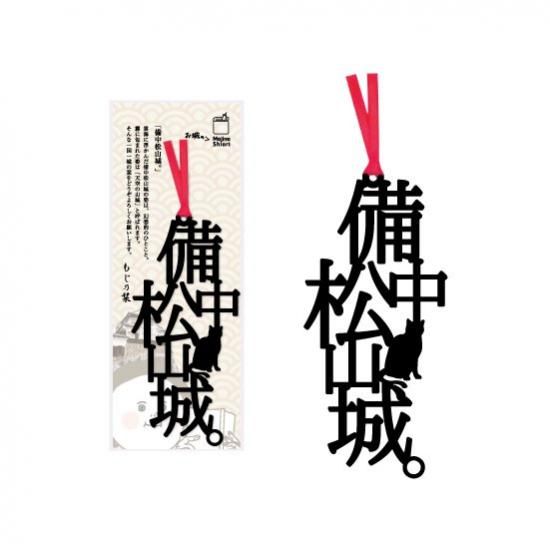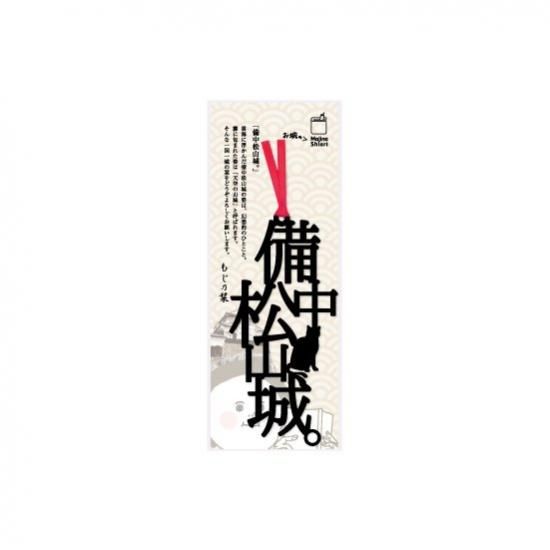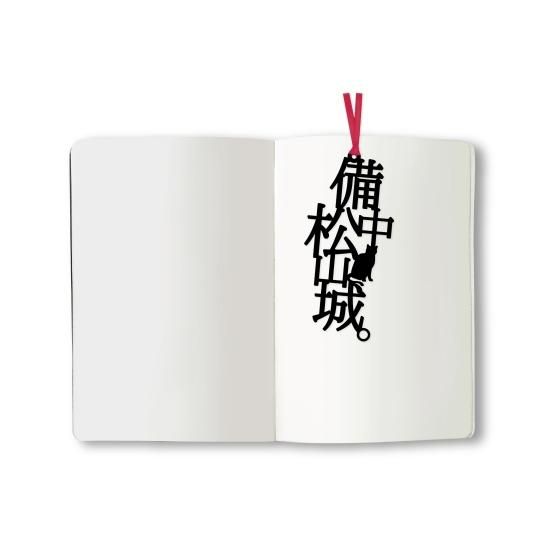
文字のお城のしおり 零-ZERO- 「備中松山城。」
雲海に浮かんだ備中松山城の姿は、幻想的のひとこと。
霧に包まれた姿は「天空の山城」と呼ばれます。
国内唯一の現存する山城として、広く知られています。
そんな一国一城の栞をどうぞよろしくお願いします。
木材パルプや綿を原料とした環境素材を採用し、耐久性・耐水性に優れたファイバーの特徴を活かすことで、言葉がフォントごと切り取られたような巧緻で美しい『文字のしおり』のデザインが実現しています。
本好きの方、お城好きの方にはもちろん、ちょっとした贈り物としても喜ばれそうです。